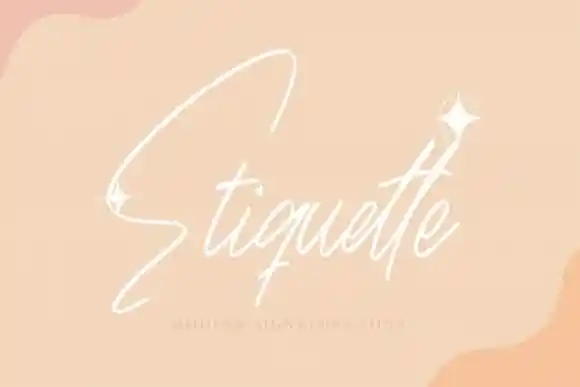
Etiquette Handwritten Font – Download Grátis
A Etiquette Handwritten Font é uma fonte de script elegante e sofisticada, perfeita para adicionarem glamour a qualquer obra de arte digital. Esta criação do designer HaftType oferece um estilo de escrita manuscrita que resulta num ar de classe e refinamento. Com suas linhas detalhadas e cuidadosamente trabalhadas, esta fonte é uma excelente adição à sua biblioteca de fontes digitais, ajudando a elevar qualquer projeto em que seja usada — seja para um site elegante, um documento profissional ou até mesmo o texto em um card de apresentação. Com o seu charme singular e alta resolução, Etiquette Handwritten Font é uma escolha ótima para quem busca estilo e sofisticação no design digital.